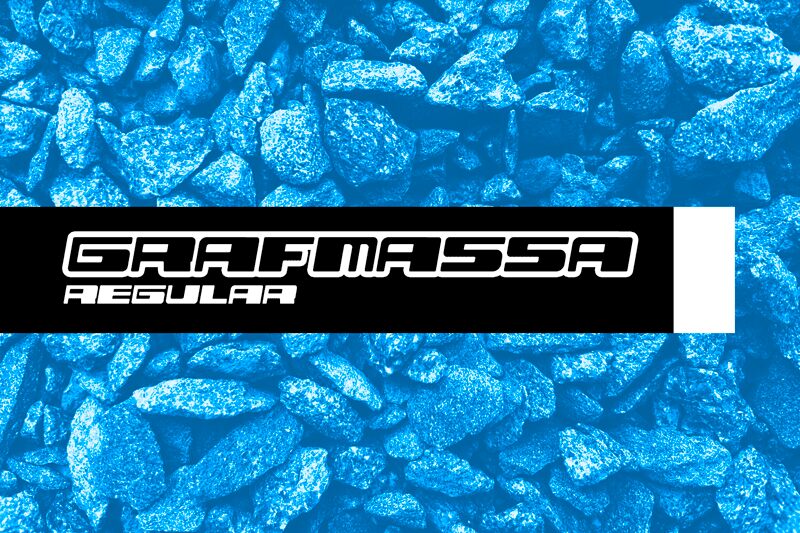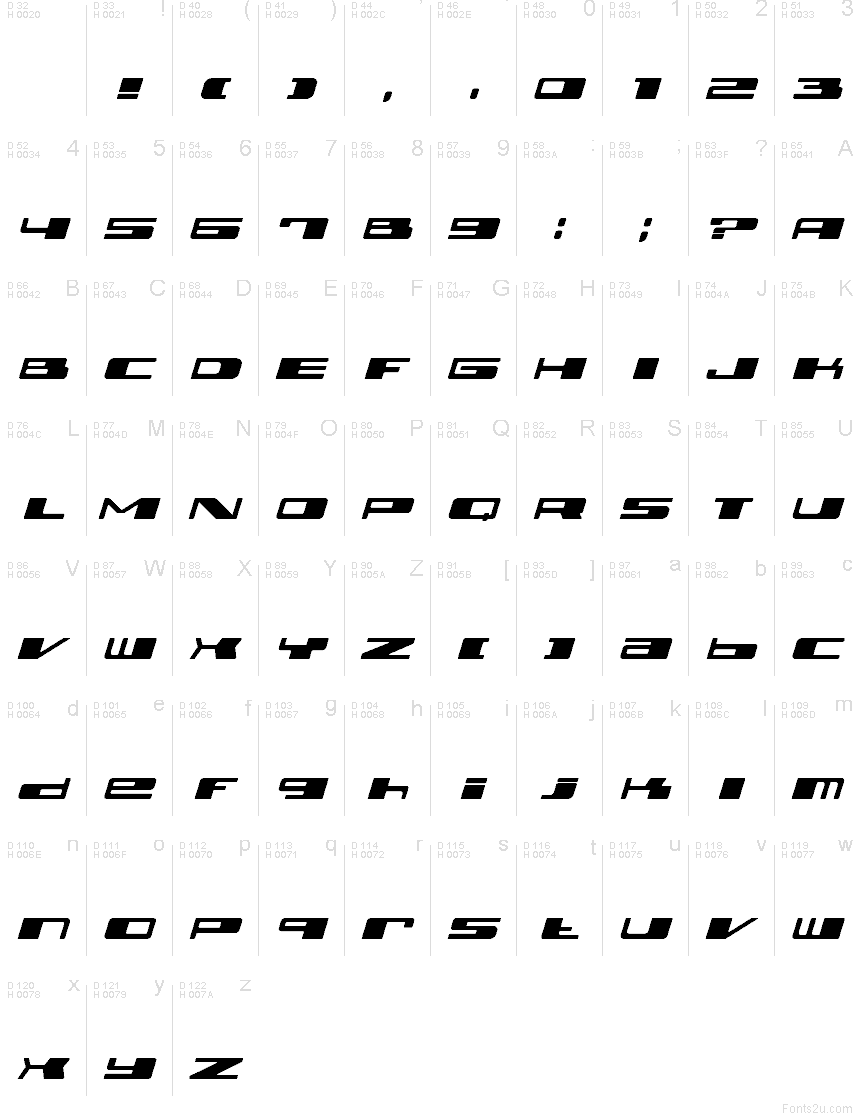
Grafmassa Oblique ist eine kostenlose, futuristische Display-Schrift aus breiten, nach vorne geneigten Buchstaben mit kompakten Formen, einem niedrigen aerodynamischen Profil und markanten geometrischen Schnitten. Abgerundete Ecken außen und lange rechteckige Öffnungen verleihen den Zeichen den konstruierten Look von Rennsport-Grafiken, Typenschildern und stromlinienförmiger Industriebeschilderung.
Ihr offensichtlichstes Anwendungsgebiet ist das Motorsport-Branding, insbesondere für moderne Team-Merchandise-Artikel, Fahrzeugbeklebungen und Event-Poster, die von Geschwindigkeit, Wettkampf, mechanischer Präzision und einer von Sponsoring geprägten visuellen Kultur leben. Dieselbe Vorwärtsneigung passt gut zu Spieloberflächen und Science-Fiction-Unterhaltung, wo die Buchstaben an Cockpit-Beschriftungen, Raumschiff-Markierungen oder Arcade-Rennembleme erinnern.
Grafmassa Oblique — Schriftpräsentation
Grafmassa
Grafmassa Oblique
Wladyslaw Borisov